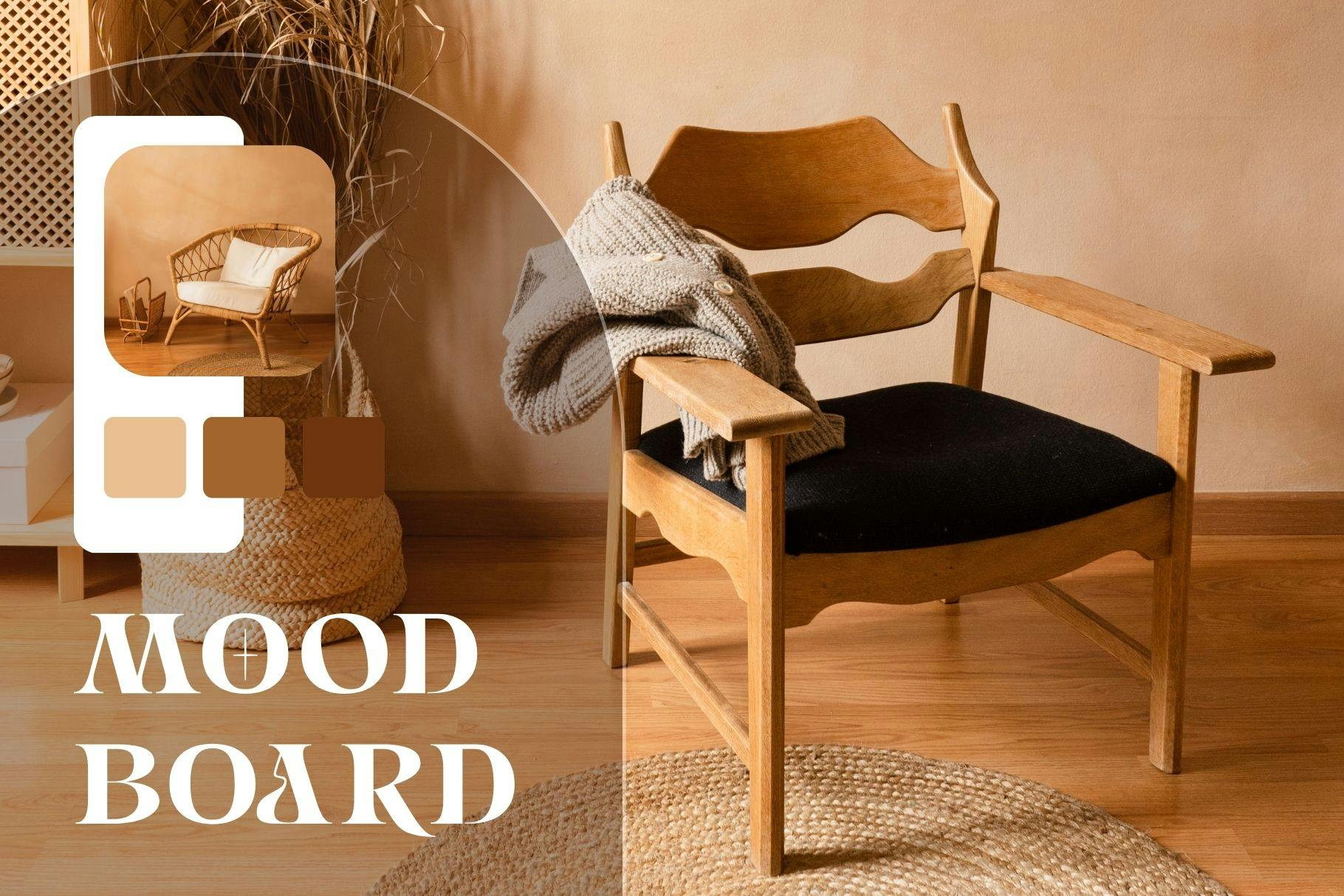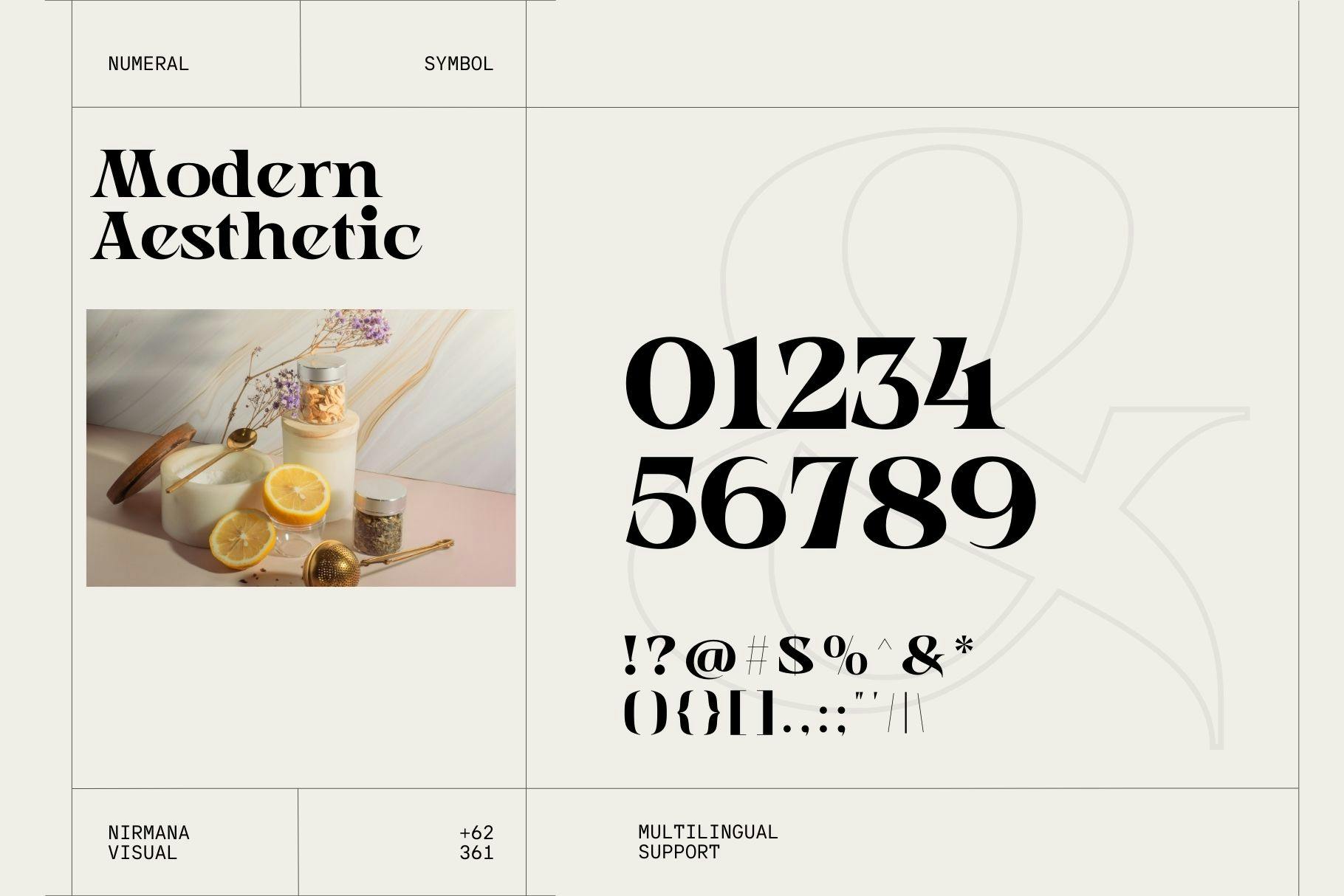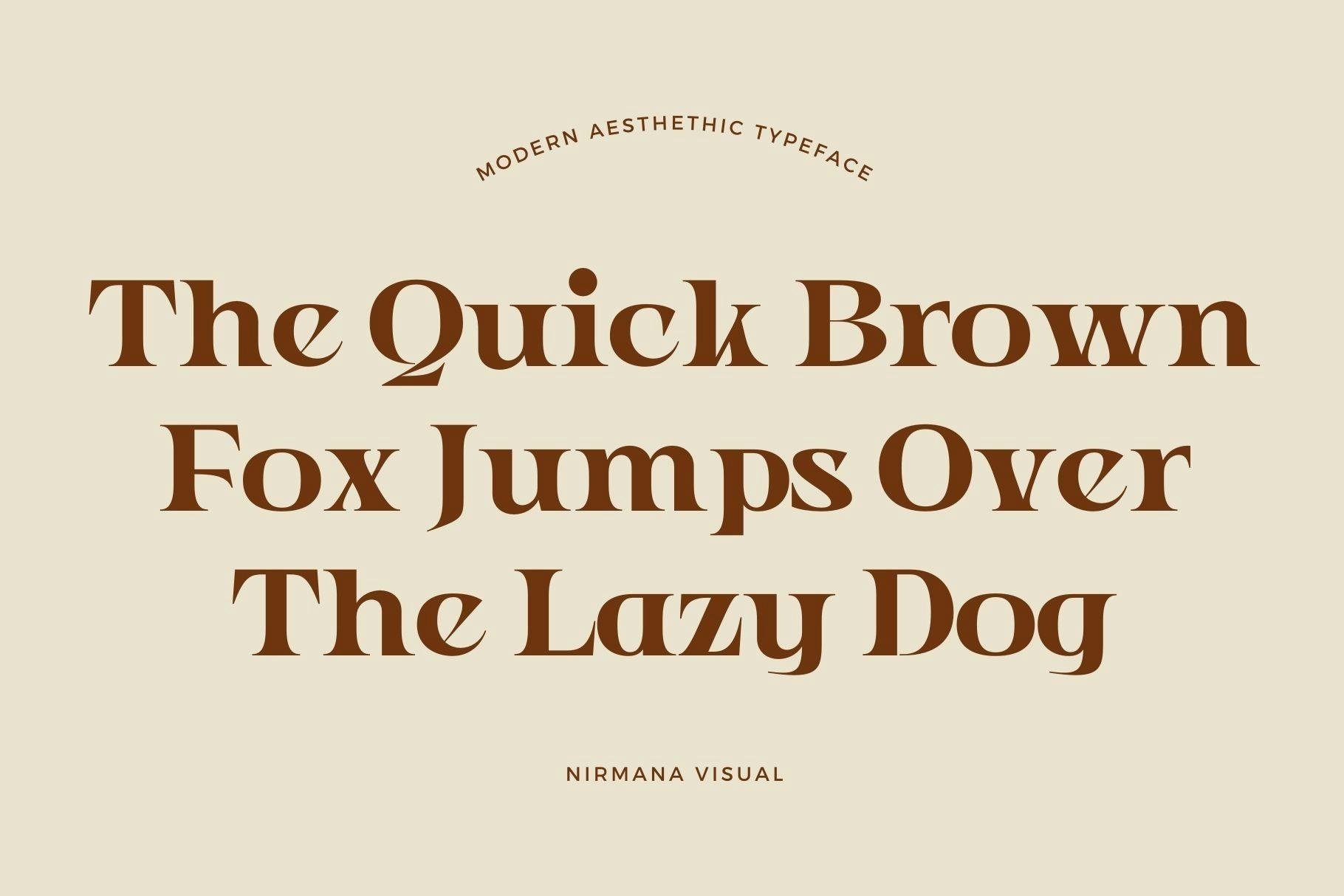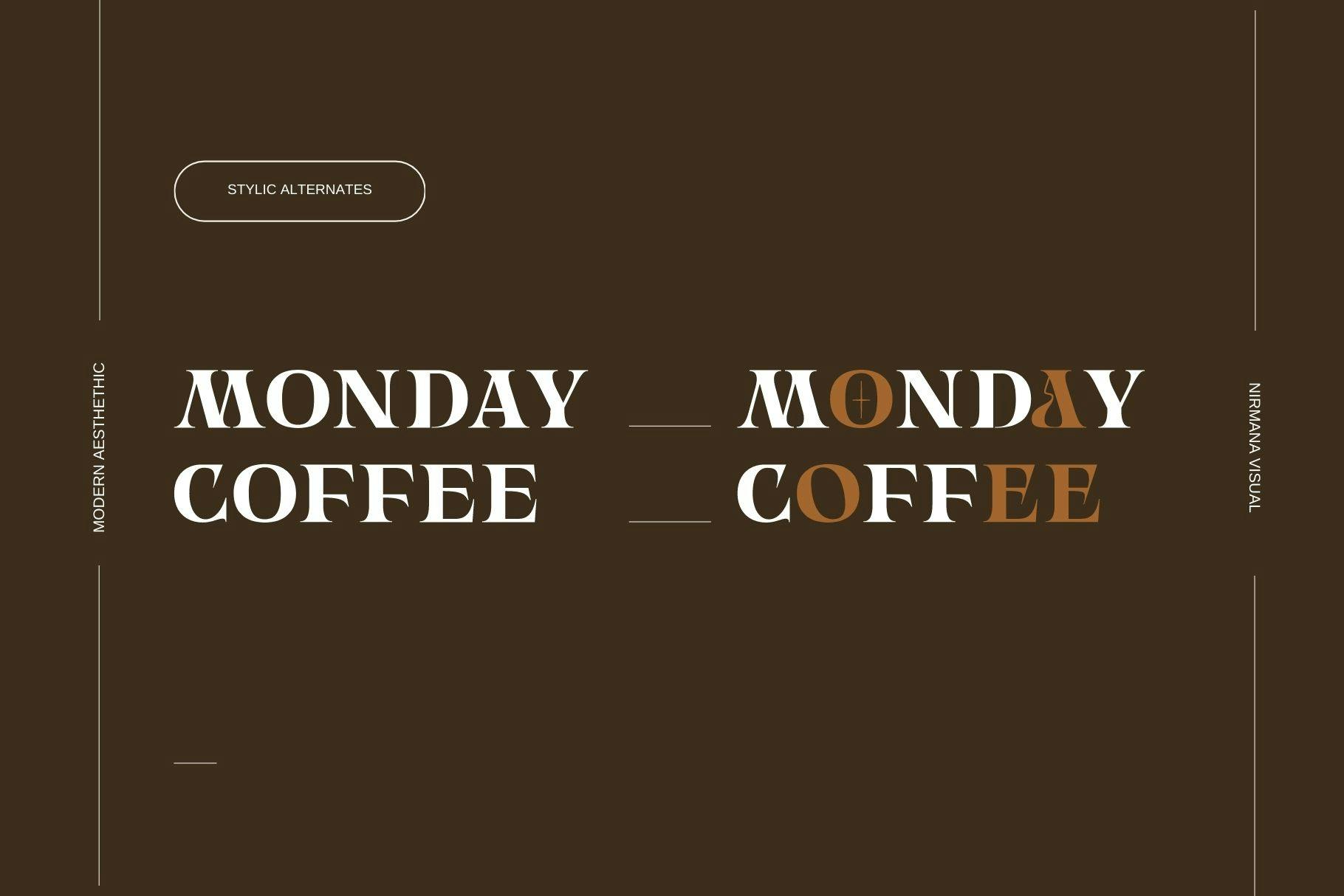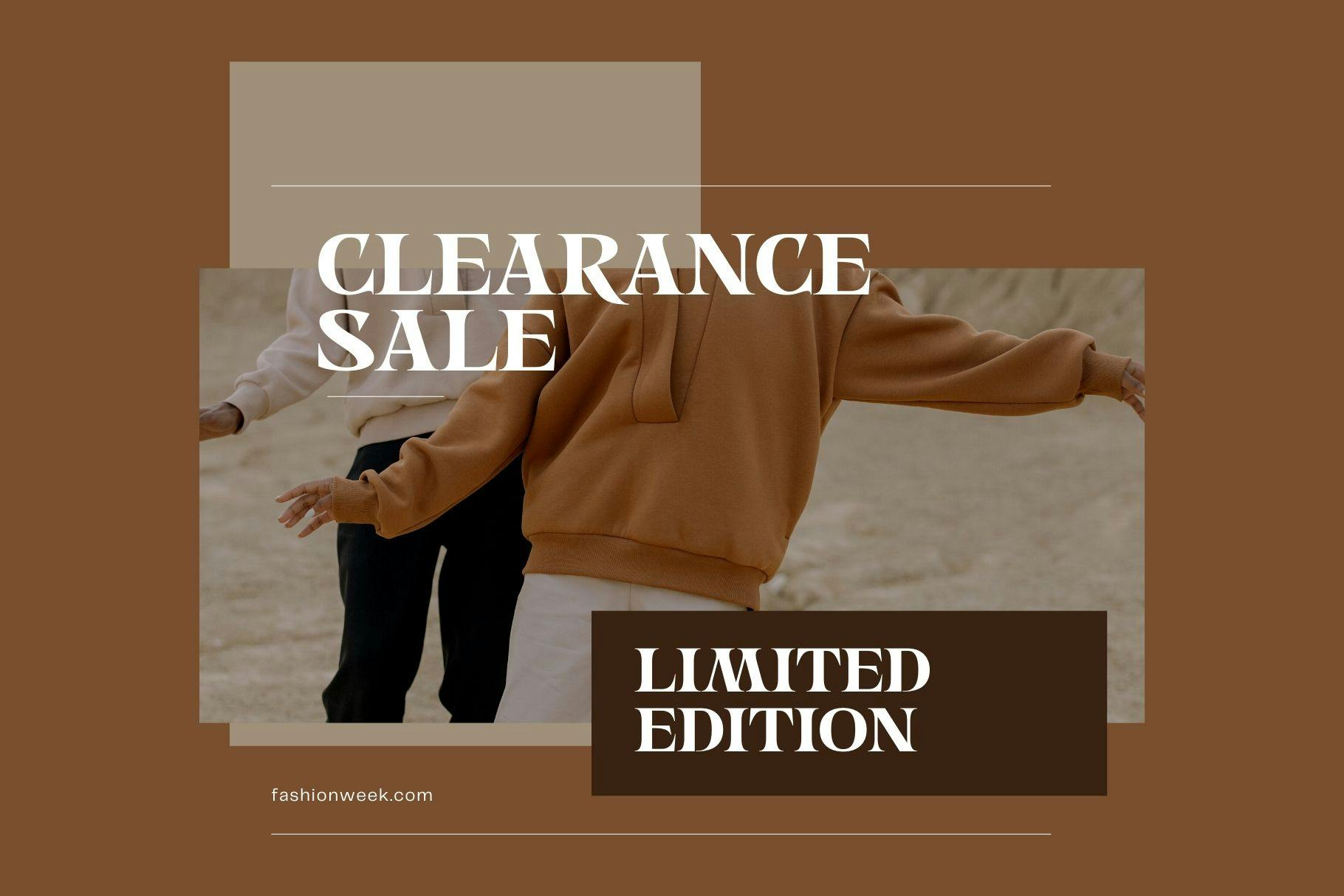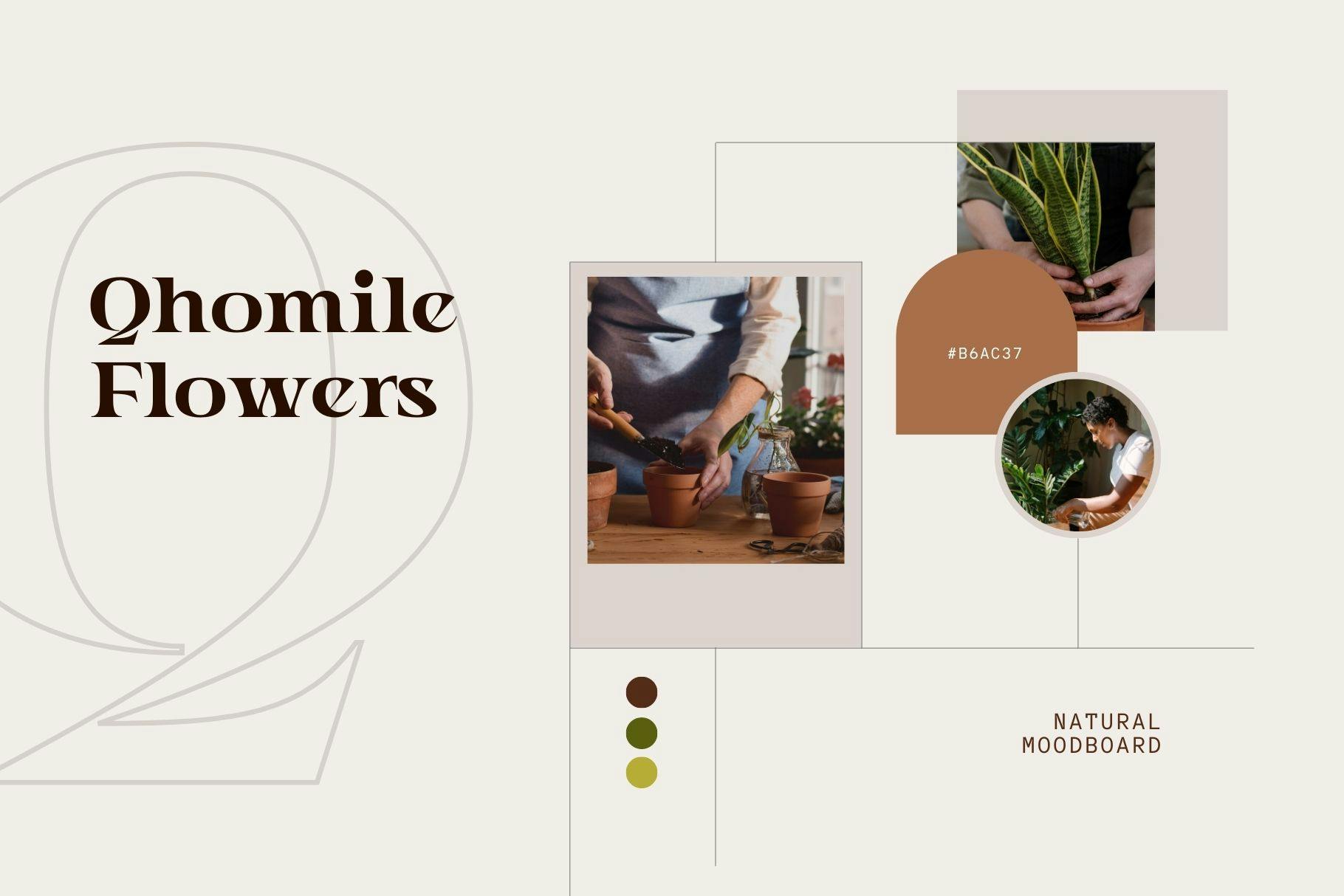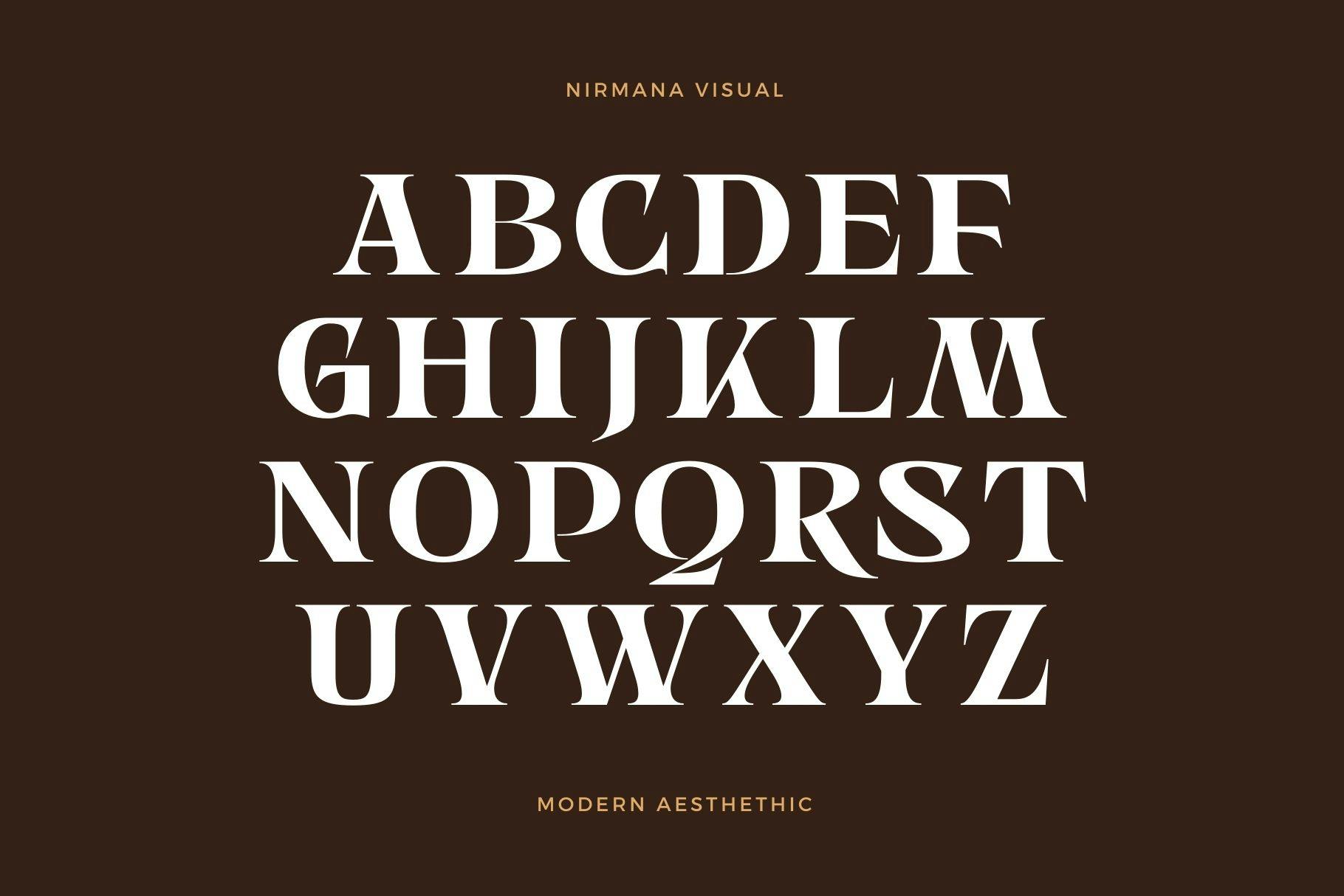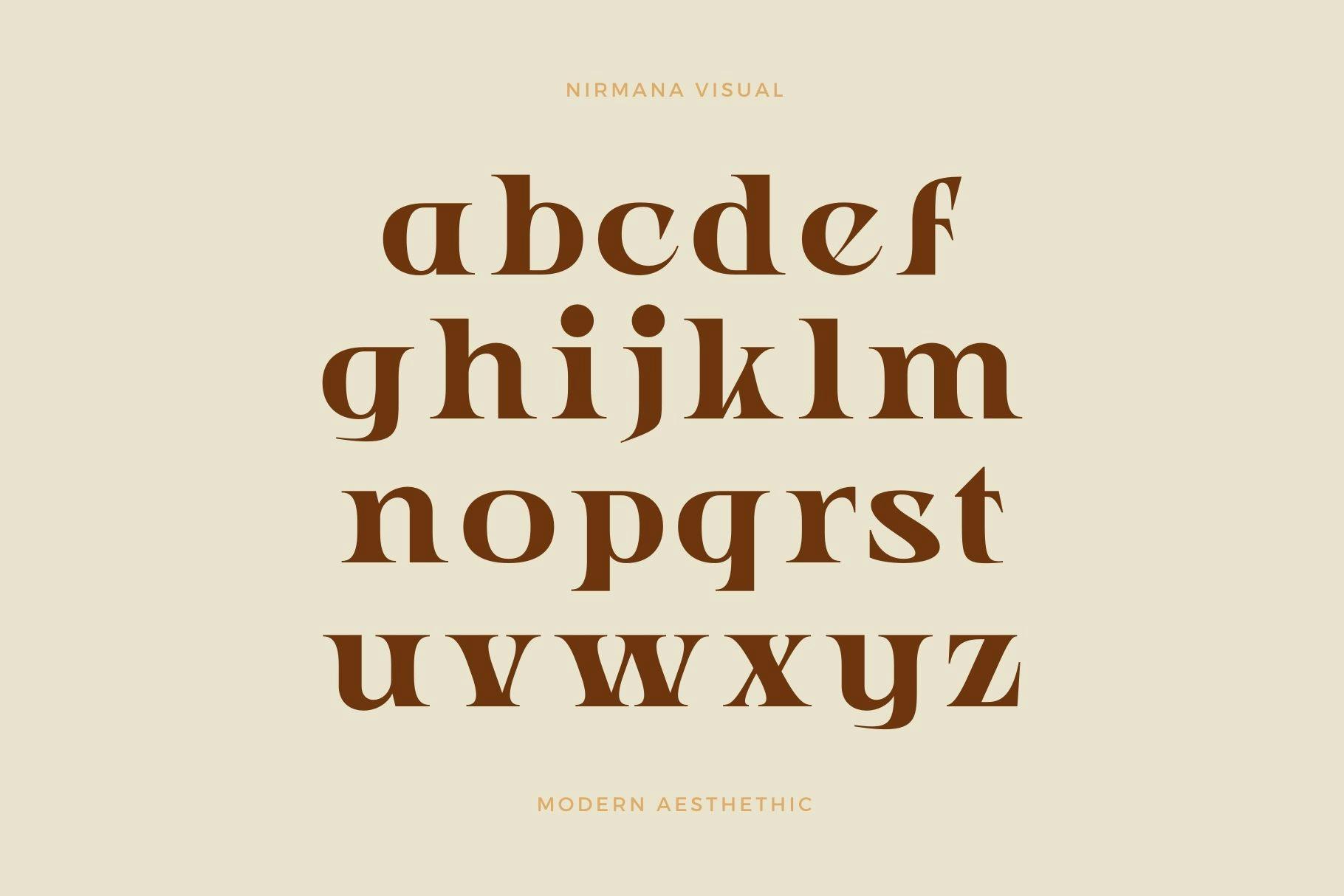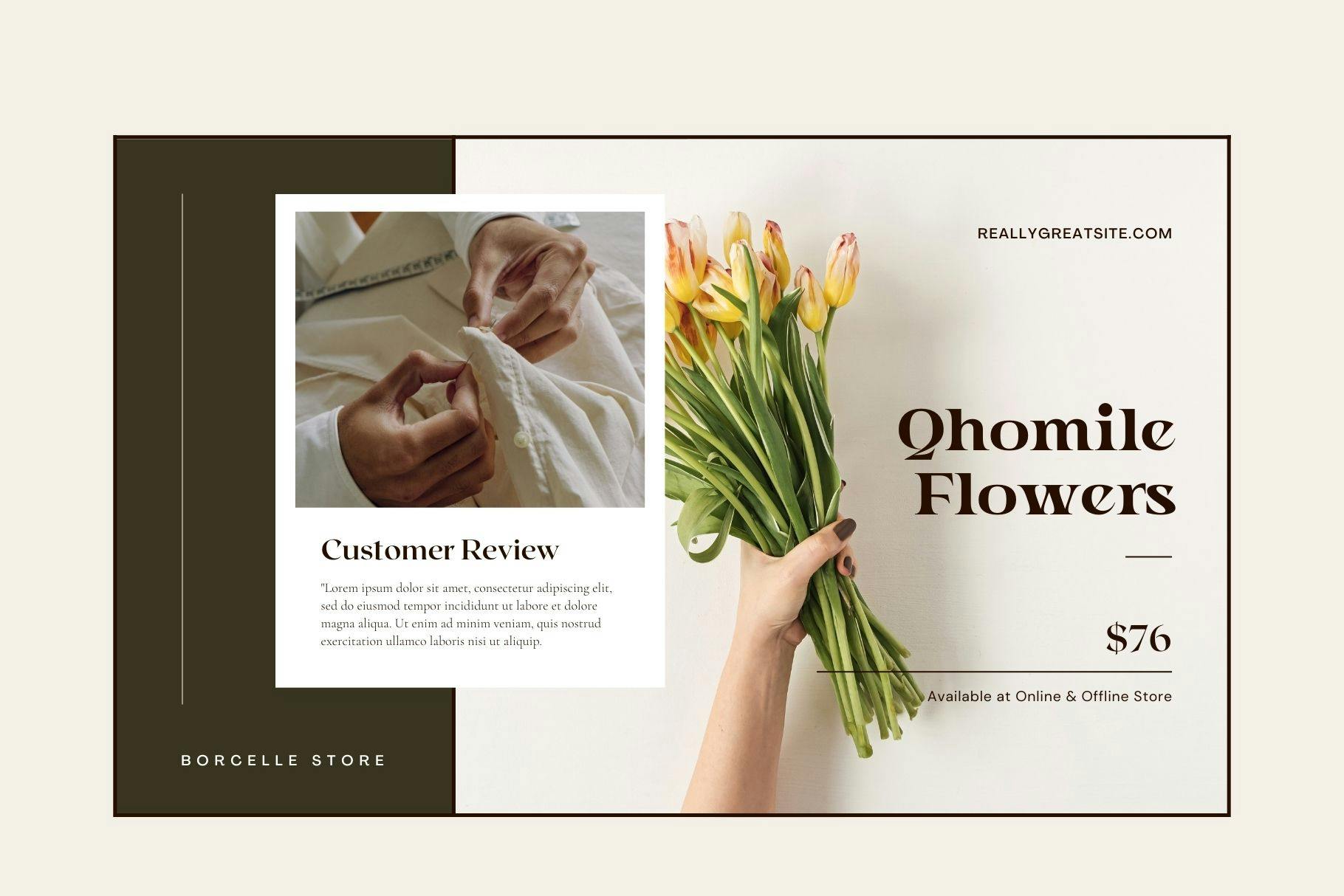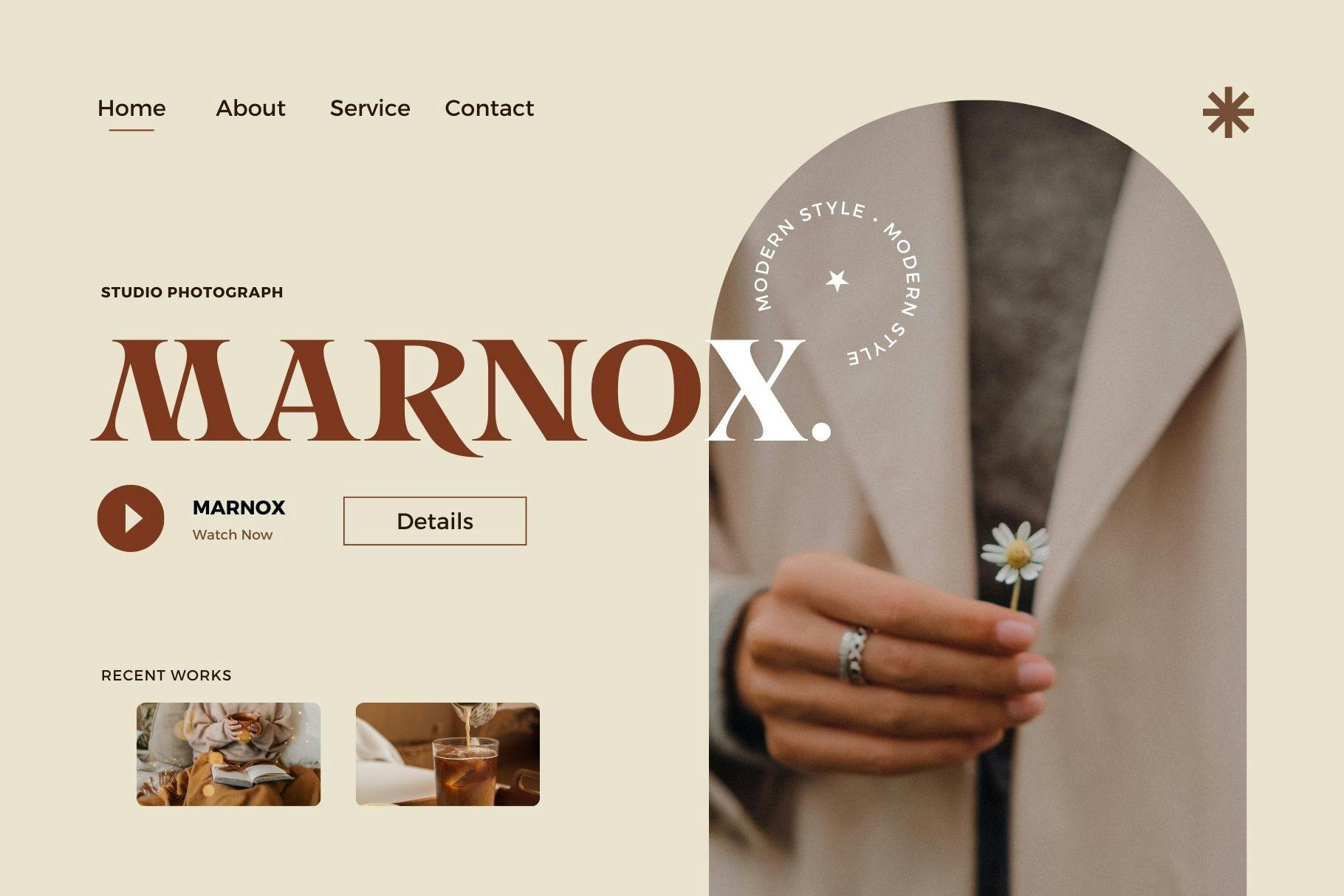
Modern Aesthetic Modern Font
فونت مدرن استتیک - فونت مدرن، تایپ‌فیس سریف دیسپلی.
فونت مدرن استتیک هارمونی زیبایی را برای پروژه‌های طراحی متنوع فراهم می‌کند، از جمله لوگو و برندینگ، پست‌های شبکه‌های اجتماعی، تبلیغات و طراحی محصولات.